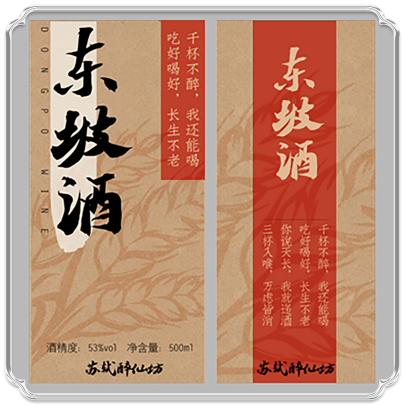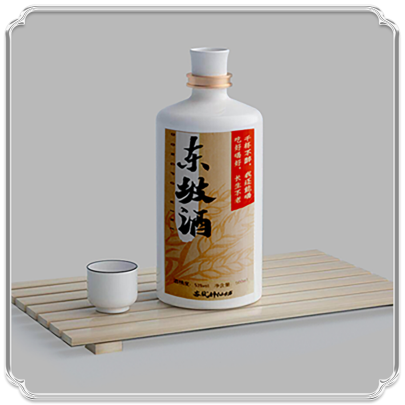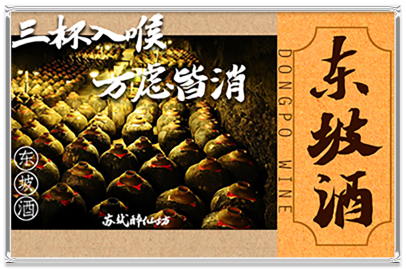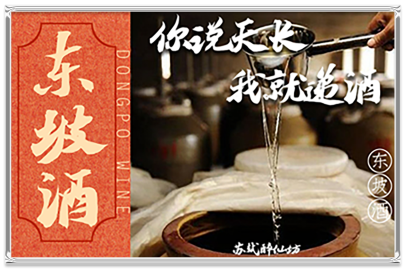
寶藏計畫
寻找汉字宝藏之旅,你想遇见谁?
五千年汉字诗卷浩渺碎片散落在历史的各个角落,
字神国风元书院搭乘时光机穿越历史长河,寻找字神留给后世的宝藏。
我们遇到了许多古代npc,并收集到了他们的碑帖真迹。
你能否读懂字里行间的暗语,将字神真迹进行还原创造?
一起开启与字神的对话
请到全国各地
把我捞回
人間如夢
豪情江月
你遇到了第一个npc——苏轼
线索:《寒食帖》
一代文豪苏轼,其书法造诣也历史垂青,
丰腴的笔画,洒脱的笔法,
你是否能感受到苏轼笔下的豁达豪放?
文人雅集
暢遊蘭亭
你遇到了第二个npc——王羲之
线索:《兰亭集序》
天下第一行书的绝世美名千古流传,
寄蜉蝣于天地,渺沧海之一粟,
王羲之于人生的喟叹依然响彻后世文人的耳畔。
百年后,
谁能与我在兰亭畅叙幽情?
不疯魔不成活
醉酒潤書
絕代狂草
你遇到了第三个npc——怀素
真迹线索:《自叙帖》
一个出家的僧人,却与美酒相伴,
他这样异于常人的疯癫状态
也造就了“天下第一草书”,
怀素还是自己种芭蕉树作为书写材料的人,
可见其对书法的热爱何其深沉。
目前,首个npc苏轼发布的任务已经完成(1/1)【字神苏轼豪放体】诞生,已成功还原,
由字体构建的虚拟世界——字神酒肆【苏轼醉仙舫】也同步开张。